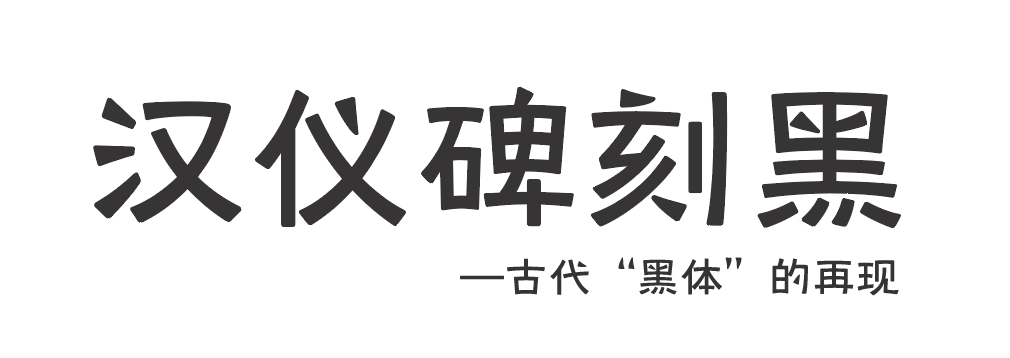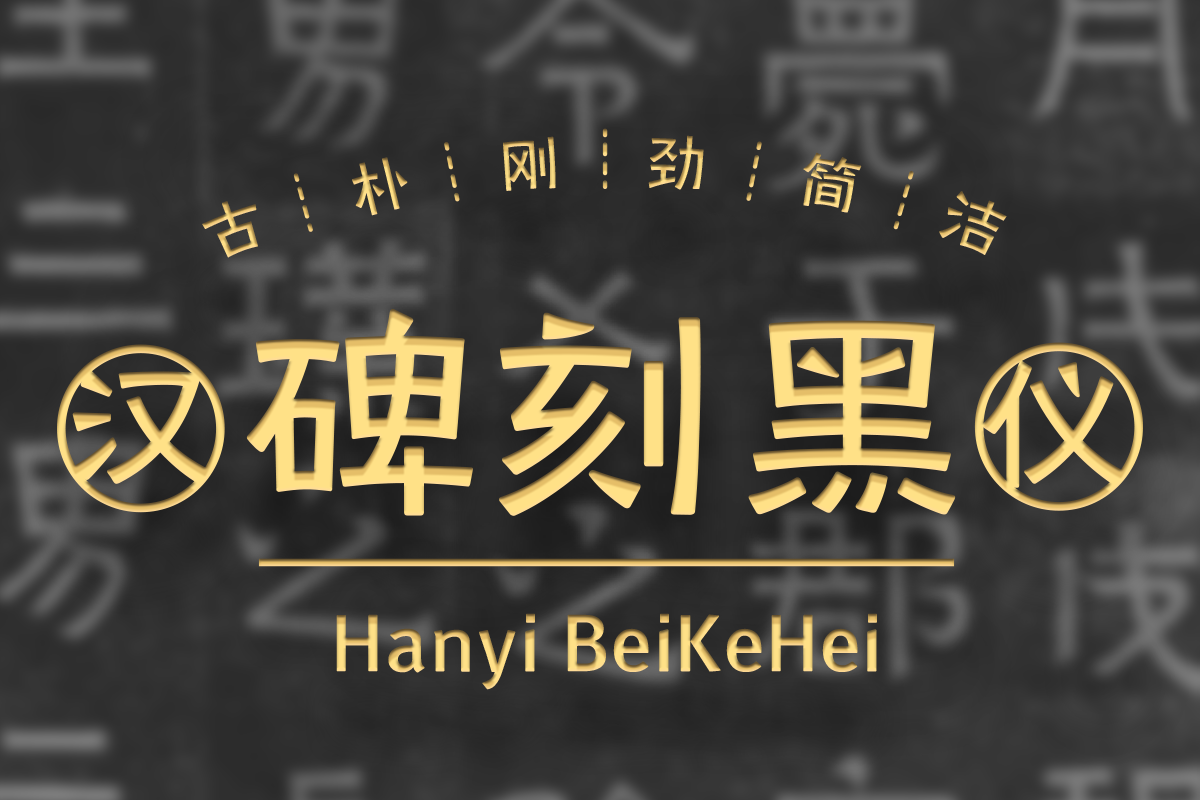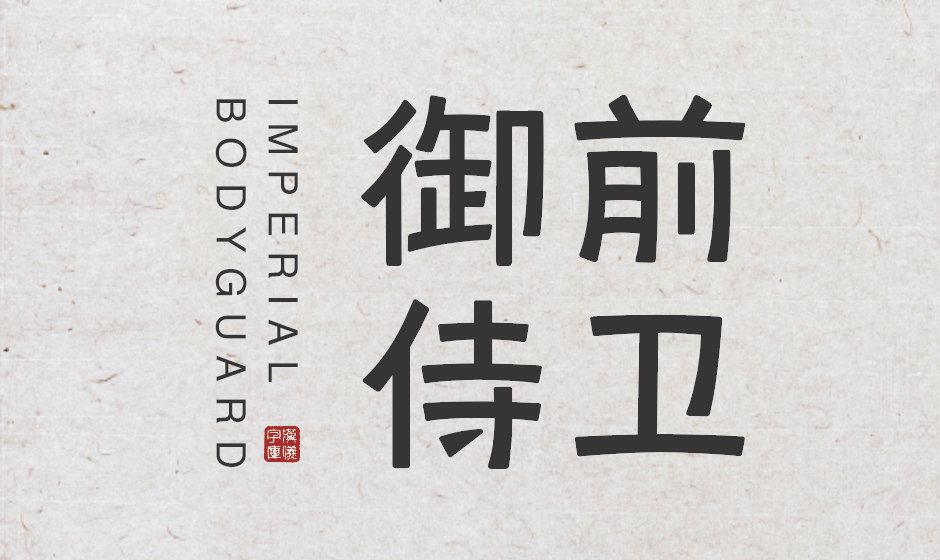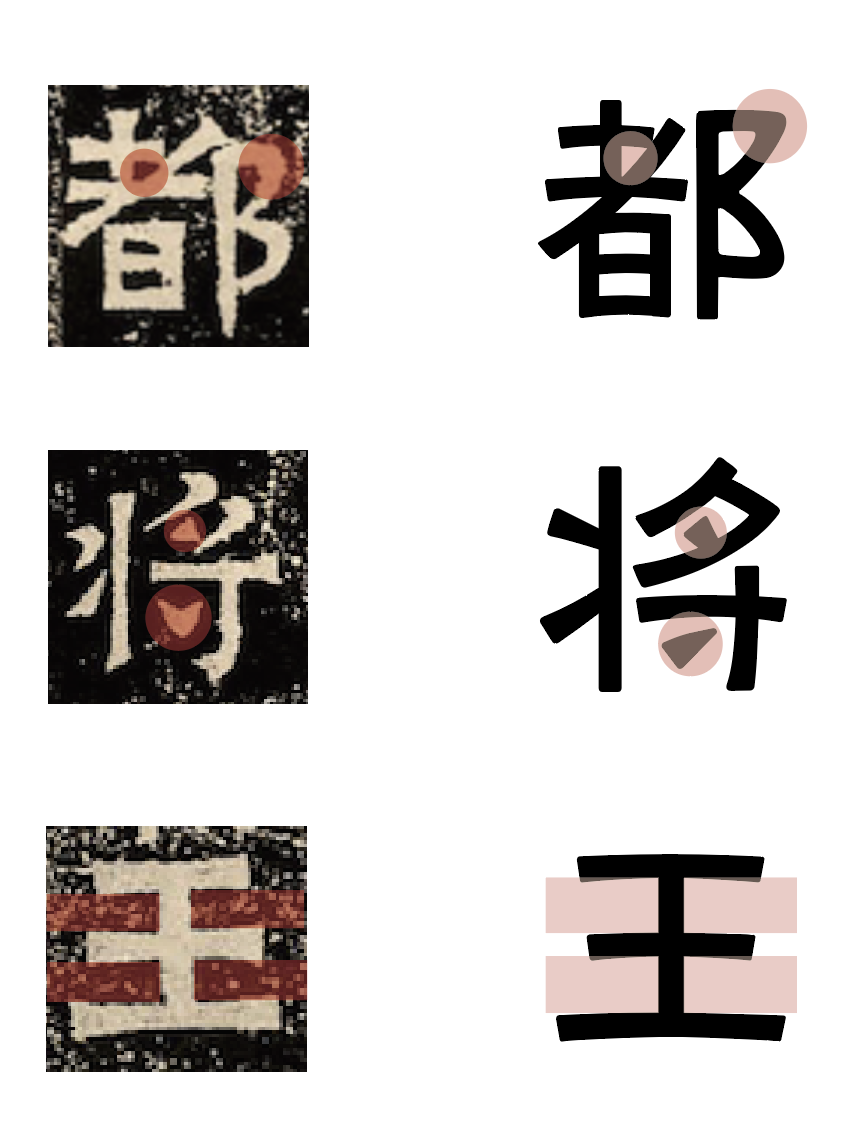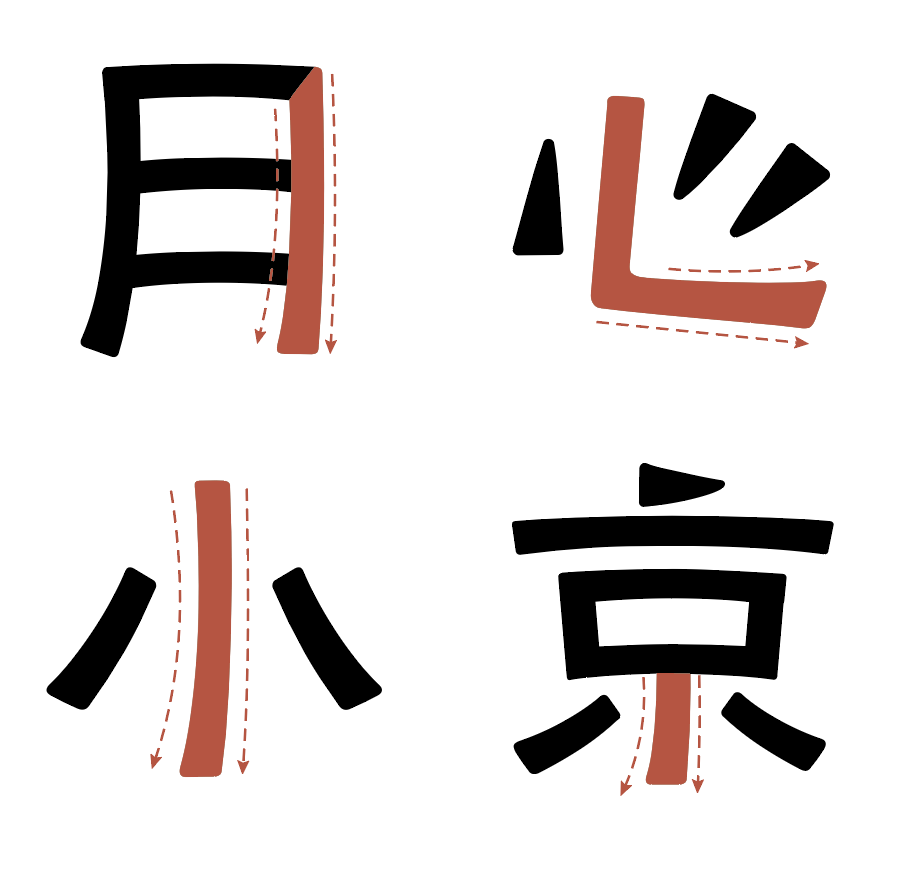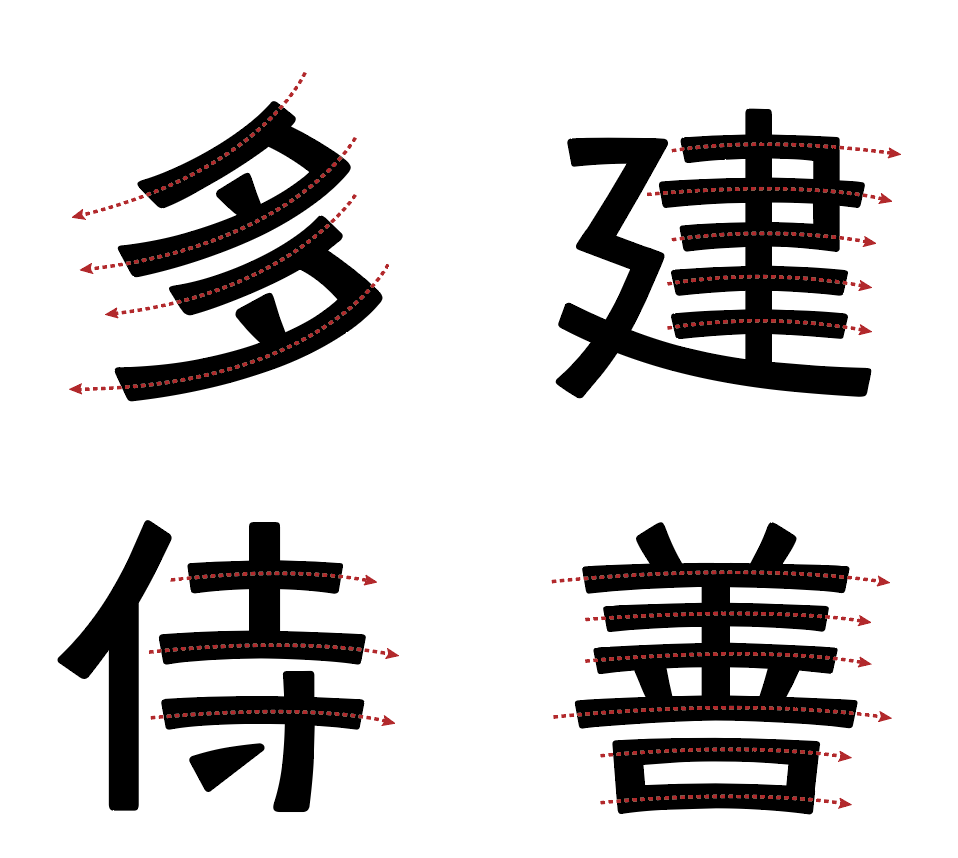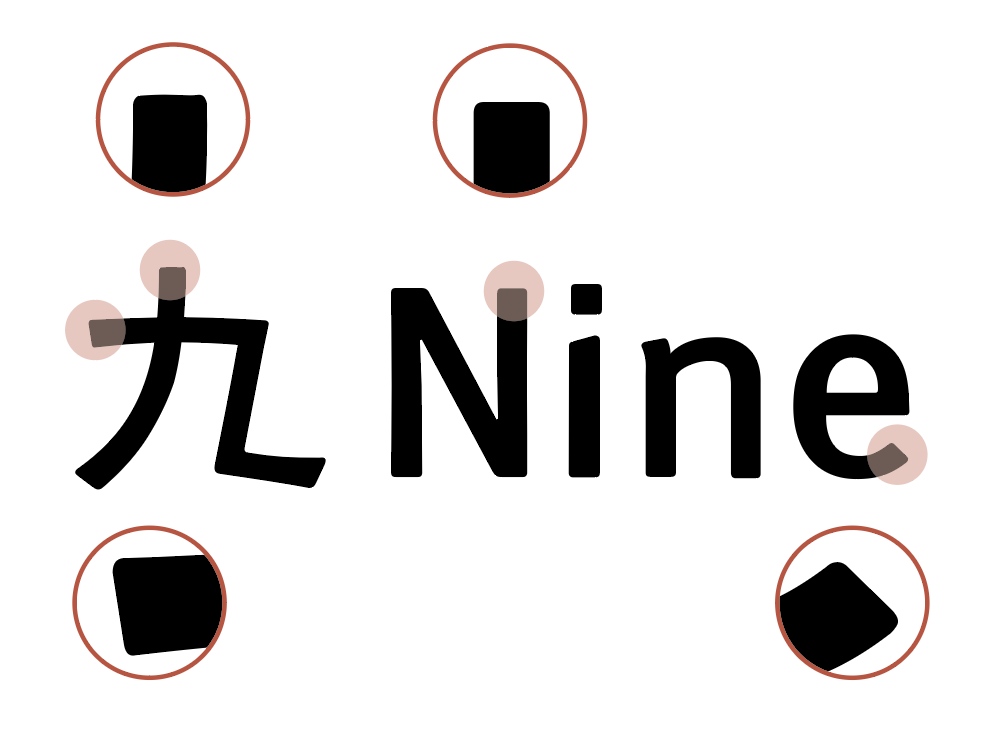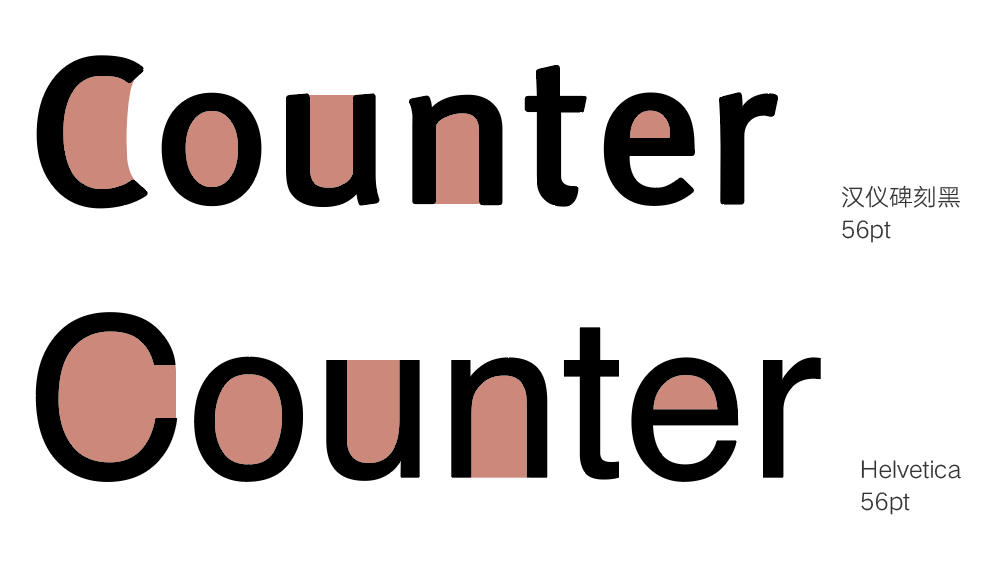
汉仪碑刻黑 | 字体之星
汉仪碑刻黑是第二届字体之星大赛的获奖作品。作者栾嘉辉通过描摹的方式掌握了汉代碑刻上文字的笔画特征和间架结构,再加以理解和设计,创造出了碑刻黑这一字体,最终获得了第二届字体之星大赛标题组—鸟海修评委奖。
汉仪碑刻黑 | 历史渊源
汉仪碑刻黑来源于王兴之夫妇墓志上的碑刻铭文,于1999年在南京北郊象山六朝时期东晋王氏家族古墓出土。这是六朝墓志书法中不可多得的精品。此志字体隶书带篆意,为《兰亭序》书法真伪的辩论提供了新佐证,对继续深入探讨六朝书法及中国书法的演变有重要意义。
汉仪碑刻黑 | 字形特点
汉仪碑刻黑字形方正严肃,规整而不刻板,凝重而有韵致。这是将东晋碑刻文字的神韵与现代审美相结合的智慧结晶。
汉仪碑刻黑 | 笔画特点
汉仪碑刻黑笔画挺拔,行气疏朗。点划之间、转折之处仍留有汉代隶书庄重古朴的遗韵。是一款既继承传统优秀文化又开启新时代的碑刻黑体。
汉仪碑刻黑将“勾”简化为直笔画。又因“勾”笔画内侧微微上挑,尾端厚重,明显区分于“横”、“竖”笔画,所以并不影响文字的识别性,反而凸显字体简洁、清劲和流畅的特点。
汉仪碑刻黑 | 曲线感
汉仪碑刻黑笔画的曲线细腻而相呼应,它减弱了碑刻线条的质朴古拙感,增添了时尚的现代感,从而使字体的适应性更强。
汉仪碑刻黑 | 西文设计
汉仪碑刻黑的西文字母参考了无衬线字体的骨骼特征,并在此基础上融合了碑刻黑中文笔画的特征。
汉仪碑刻黑的西文字母字怀较小,字形较窄。这种设计增强了文字的可读性和易读性。
汉仪碑刻黑 | 排版效果